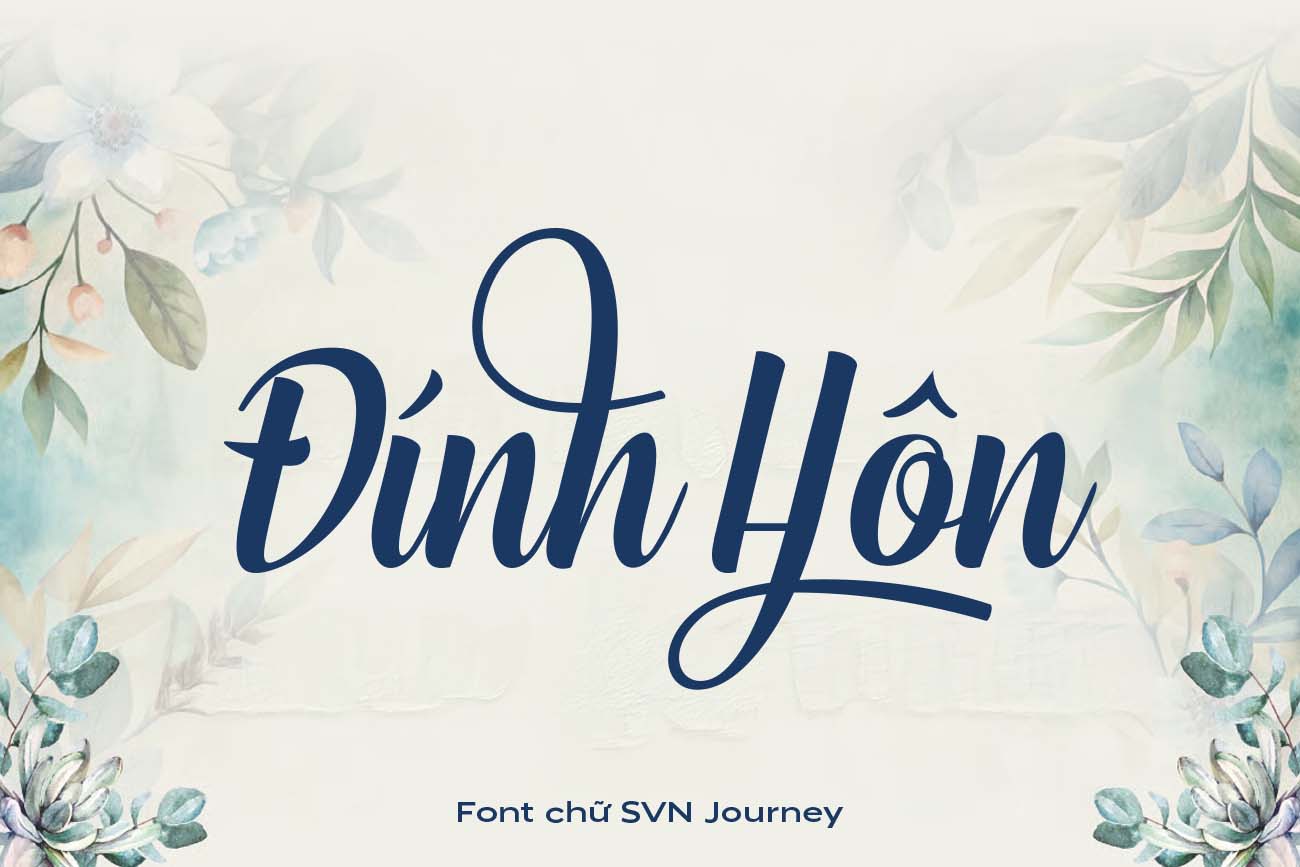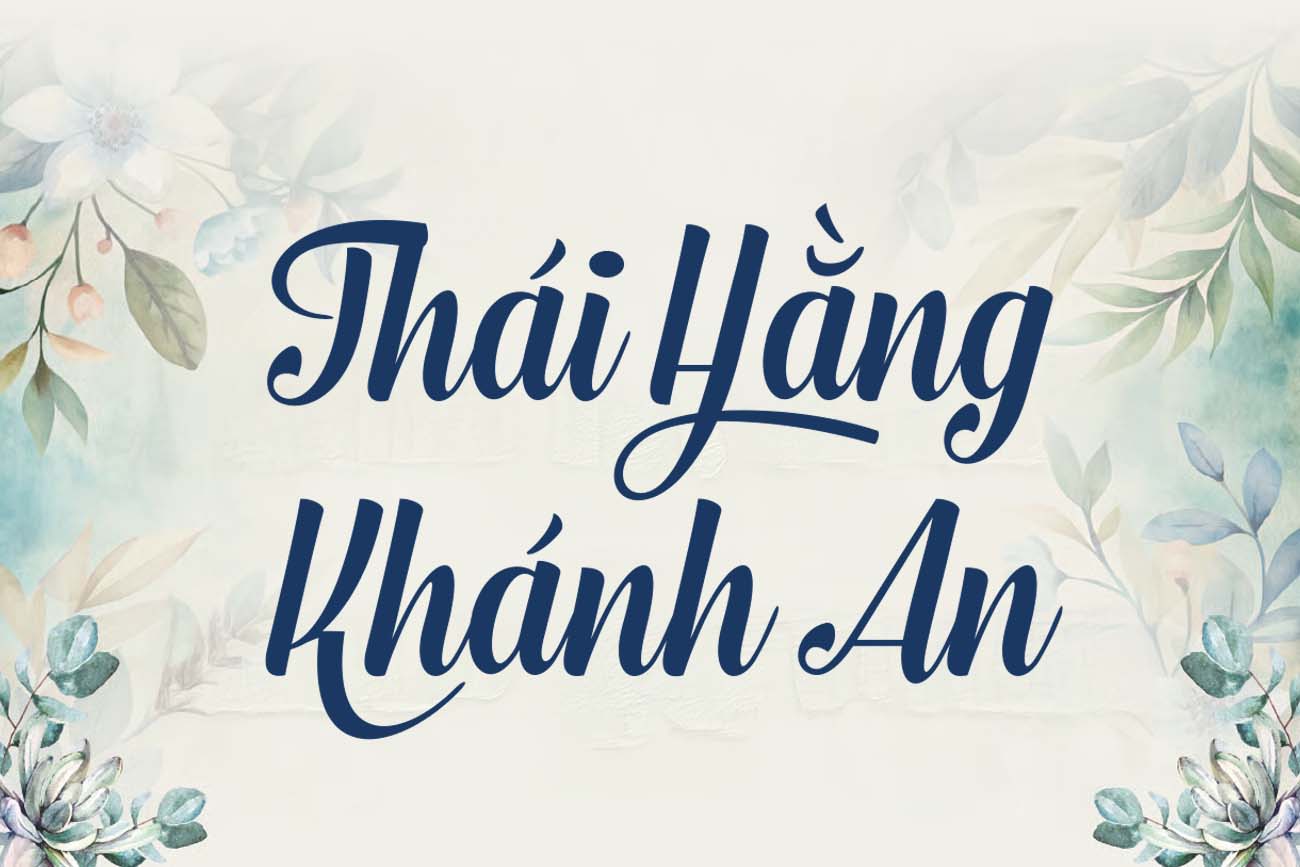
Bạn đang tìm một font chữ viết tay đẹp, nhẹ nhàng và tinh tế để thiết kế thiệp mời, lời chúc, hoặc trang trí các sự kiện đặc biệt? Font SVN Journey chính là lựa chọn đáng giá. Đây là bản Việt hóa của font Journey Script do BrandSemut Studio (Indonesia) thiết kế – một studio nổi tiếng với các bộ font viết tay mang đậm cảm xúc và tính nghệ thuật.
Nguồn gốc bộ font SVN Journey
Font gốc Journey Script được tạo nên bởi BrandSemut Studio, với mục tiêu mang đến một kiểu chữ viết tay vừa mềm mại, hiện đại, lại dễ ứng dụng cho các thiết kế cá nhân và thương mại. Font sử dụng nét bút lượn cong nhẹ, bay bổng nhưng kiểm soát tốt, tạo cảm giác mượt mà và lôi cuốn thị giác mà không bị rối hay quá cách điệu.
Một điểm mạnh đáng chú ý: bộ font này sở hữu hơn 350 glyph, trong đó có hàng chục ký tự thay thế (alternates), chữ hoa cách điệu, và các dạng kết nối chữ độc đáo giúp bạn biến hóa linh hoạt trong từng thiết kế. Các ký tự đặc biệt (ligatures) và stylistic sets cho phép người dùng cá nhân hóa phong cách chữ rất hiệu quả.
Việt hóa kỹ lưỡng bởi Team SVN
Phiên bản Việt hóa – SVN Journey do Team SVN Fonts thực hiện đã bổ sung đầy đủ dấu tiếng Việt, đảm bảo font hoạt động hoàn hảo trong mọi thiết kế dùng tiếng Việt: từ chữ hoa đặc biệt như “Đ” cho đến dấu sắc, huyền, hỏi, ngã, nặng – đều được thiết kế hài hòa với tinh thần gốc.
Đặc biệt, việc giữ nguyên các glyph thay thế và ligatures cũng giúp người dùng tại Việt Nam có thể tận dụng tối đa khả năng sáng tạo mà font mang lại.
Điểm nổi bật của font SVN Journey
• Nét viết tay bay bổng, tạo cảm giác thân thiện và lãng mạn
• Hơn 350 glyph, bao gồm nhiều chữ cái thay thế, stylistic alternates, ligatures
• Dễ dàng sử dụng trong thiết kế thiệp cưới, poster, banner, lời chúc, ảnh kỷ niệm
Gợi ý ứng dụng
Font SVN Journey phù hợp với nhiều mục đích như:
• Thiệp cưới, lễ đính hôn, thư mời sang trọng
• Bìa album ảnh, backdrop sự kiện, quote typography
• Tiêu đề blog, nội dung mạng xã hội dịp đặc biệt
• Bao bì sản phẩm, nhãn handmade, thương hiệu cá nhân
Nếu bạn đang tìm một font chữ viết tay Việt hóa vừa đẹp, vừa có chiều sâu thiết kế, lại hỗ trợ tiếng Việt hoàn chỉnh – thì SVN Journey là một lựa chọn bạn không nên bỏ lỡ.